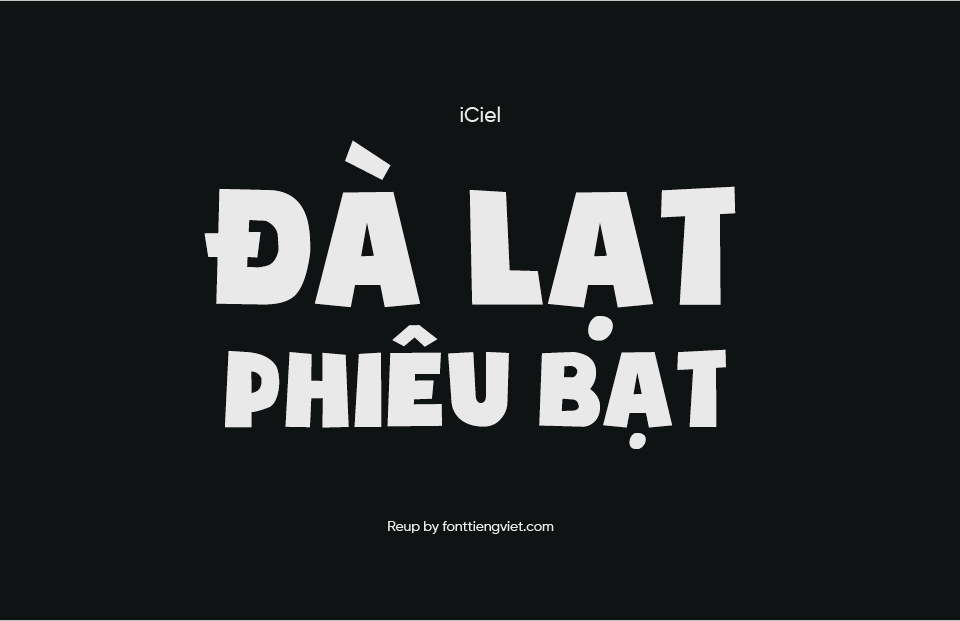
Font việt hóa iCiel Soup of Justice
Giới thiệu về Font việt hóa iCiel Soup of Justice
Trong thế giới sáng tạo, việc lựa chọn một Font Miễn Phí phù hợp là yếu tố then chốt để tạo nên sức hút cho tác phẩm. Font việt hóa iCiel Soup of Justice là một trong những bộ phông chữ tiêu biểu, mang phong cách mạnh mẽ và đầy cá tính. Được lấy cảm hứng từ các biểu tượng siêu anh hùng kinh điển, bộ font này sở hữu những đường nét dày dặn, bo tròn tinh tế nhưng vẫn giữ được sự chắc chắn cần thiết. Phiên bản việt hóa bởi iCiel giúp các nhà thiết kế tại Việt Nam dễ dàng sử dụng đầy đủ các dấu câu mà không lo lỗi hiển thị, mang lại sự đồng nhất tuyệt đối cho nội dung văn bản.
Ưu điểm nổi bật của Font việt hóa iCiel Soup of Justice
Phong cách thiết kế độc đáo và hiện đại
Đặc điểm nhận diện lớn nhất của Font việt hóa iCiel Soup of Justice chính là sự kết hợp giữa nét chữ đậm và các góc bo mềm mại. Điều này tạo nên cảm giác thân thiện nhưng không kém phần uy lực, rất phù hợp cho các tiêu đề lớn, banner quảng cáo hay bao bì sản phẩm. Font chữ này thường được các bạn học sinh sử dụng trong các bài thuyết trình hoặc làm poster sự kiện trường học để tăng thêm phần sinh động và bắt mắt.
Khả năng ứng dụng linh hoạt trong nhiều lĩnh vực
Không chỉ giới hạn trong mảng đồ họa giải trí, bộ font này còn cực kỳ hiệu quả khi làm logo hoặc các ấn phẩm truyền thông mạng xã hội. Nhờ khoảng cách giữa các chữ cái được căn chỉnh hợp lý, người xem có thể dễ dàng đọc được nội dung ngay cả ở khoảng cách xa hoặc trên màn hình điện thoại nhỏ.
Cách sử dụng Font việt hóa iCiel Soup of Justice hiệu quả
Để phát huy tối đa vẻ đẹp của Font việt hóa iCiel Soup of Justice, bạn nên kết hợp nó với các màu sắc rực rỡ hoặc hiệu ứng đổ bóng 3D. Việc sử dụng font này làm tiêu đề chính và phối hợp với một font chữ không chân đơn giản cho phần nội dung sẽ tạo nên sự cân bằng hoàn hảo. Hy vọng qua bài viết này, bạn sẽ có thêm một công cụ hữu ích cho kho tàng sáng tạo của mình tại Font Miễn Phí, Font Việt Hóa, Font việt hóa iCiel Soup of Justice để hoàn thiện các dự án cá nhân ấn tượng nhất.